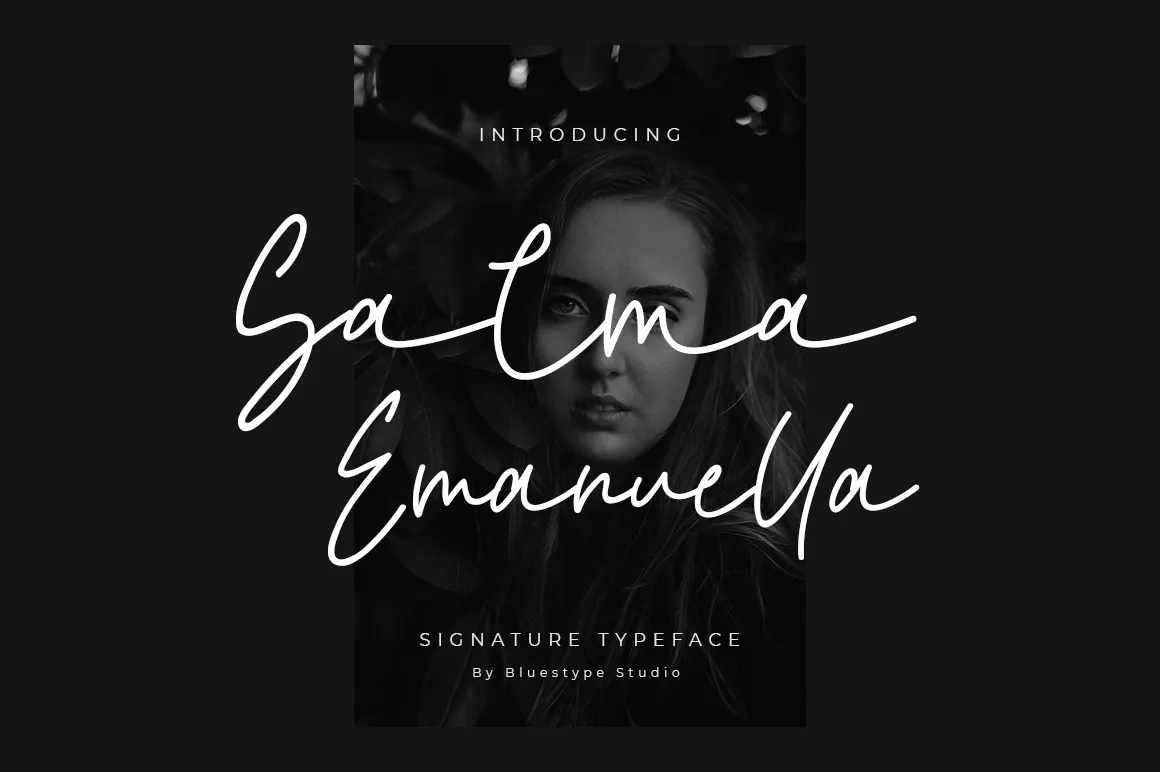
A Salma Emanuella é uma elegante tipografia manuscrita monoline que transmite modernidade e simplicidade. Sua característica única permite que você inove nas criações digitais, criando projetos incríveis que se destacam. Com um design simples mas sofisticado da Bluestype Studio, essa fonte deixa sua marca mais marcante em qualquer projeto digital ou impresso. Seja para gráficos e imagens, designs web ou até mesmo letras de música, a Salma Emanuella é perfeita para aqueles que valorizam estética e criatividade. Inspirada pela simplicidade moderna, essa fonte atinge todos os níveis, tornando-se uma escolha essencial tanto para profissionais quanto para iniciantes no universo da design gráfico. Download já e veja como ela vai transformar sua arte digital!